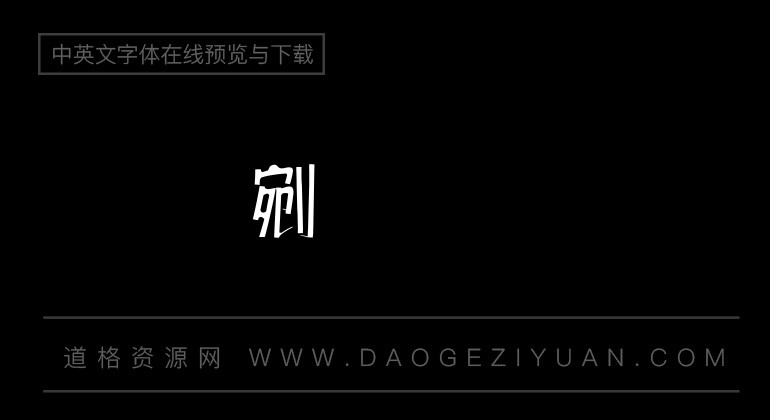
富汉通中角报体繁
富汉通中角报体繁是一款繁体字设计,由台湾著名字体设计师陈思宇设计,它是一款经典的繁体字体,以其优美的线条、精致的曲线、精细的细节和清晰的结构,呈现出一种古典、优雅的风格。它有着清晰的笔画,流畅的线条,细腻的曲线,清晰的结构,让字体看起来更加精致优雅,能够满足不同的设计需求,是一款非常受欢迎的字体。
富汉通中角报体繁是一款非常不错的手写艺术字体,具有很好的视觉感,适合于文化类的宣传设计、商业类品牌的广告和产品包装设计以及个性化文字排版等较多场景。
富汉通中角报体繁字符映射图